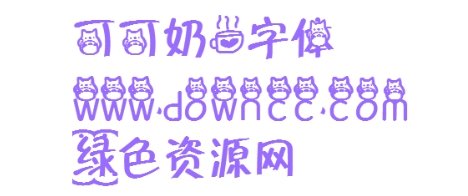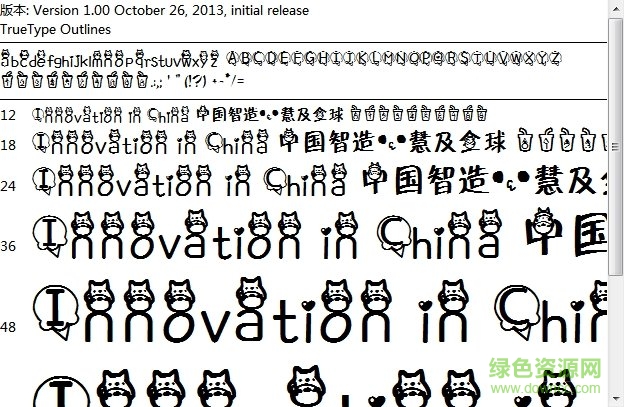
可可奶茶字體ttf是一款有著奶茶裝飾和點綴的可愛卡通字體,讓文字變得有聲有色起來,用于制作吸引兒童目光和興趣的產(chǎn)品上很有幫助,快來綠色資源網(wǎng)試試吧!
可可奶茶字體加上奶茶杯,龍貓等小元素,并將一些字體用形象的簡筆畫進行替換,非常呆萌可愛,用于制作兒童內容的文字產(chǎn)品更加吸引觀眾的眼球哦,在平面設計上、海報設計上也有增益!